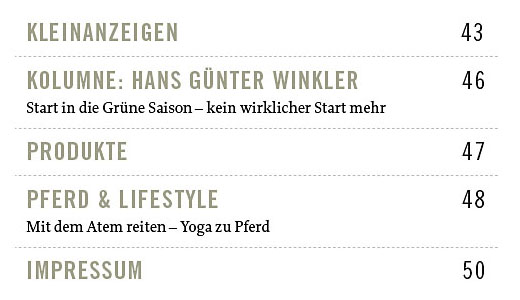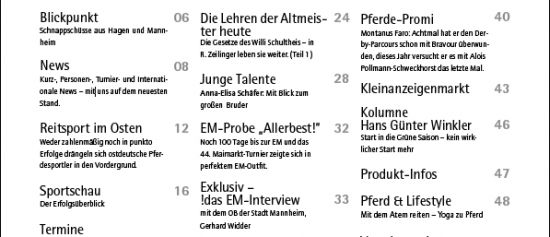
Frage an Typocracks: Zulässig oder besser nicht?
Bei der Gestaltung eines Inhaltsverzeichnisses eines Magazines stehe ich vor der Frage, ob die gewählte Schriftmischung zulässig oder doch ein absolutes "no go" ist:
Eine Rotis Semi Sans 55 (15 Punkt) als Headline mit einer ATQuaySans book (9 Punkt) für den Fließtext?
Eventuelle Alternativen?
Wobei die ATQuay die Standard Schrift des Magazins ist.
Hi nicki, hast du bilder?
Mein erster Reflex bei Rotis ist ja immer ein zartes NEEIIN!! und Quay ist auch sehr eigen.
Die Problematik ist hierbei insgesamt, dass ursprünglich 2 Seiten Inhalt jetzt auf 1 Seite sollen - inclusive Bildern, die ich jetzt obendrüber positioniert habe...
Im Anhang ein Sceenshot von einem Ausschnitt der Seite.
von der quay kann ich wenig erkennen, es scheint aber zu harmonieren. Warum nimmst du nicht auch die Quay in den Überschriften?
Wenn du Platz sparen musst, kannst du bestimmt noch was bei der Anordnung der Seitenzahlen reißen und die Zwischenzeilen halbieren.
...tja - die zweite Schrift war ursprünglich eine "Notlösung", da ich keinen "light"- Schriftschnitt von der ATQuay habe...
Hier nochmal 2 Ausschnitte - vielleicht erkennt man das besser....
Nur als Möglichkeit: Für die Überschriften die Quay und im Text dann Trade Gothic oder News Gothic? So ganz rund laufen die beiden meiner Meinung nach nicht zusammen.
wenn dann eher die trade/news gothic für die headlines ...
im fliesstext ist die quay sicher etwas vorteilhafter!
..o.k. - vielen Dank erstmal - woran kann ich das festmachen, ob etwas harmoniert, oder nicht?
Bei mir ist es oft Gefühlsache - ich würde es aber gerne wissen, eine Regel kennen, ein Gesetz anwenden.
Die Aussagen in Standardwerken sind diesbezüglich nicht einheitlich dargestellt...
Jedenfalls kann ich für mich keine Regel ableiten.
Ein schwieriges Thema.
...hier mal ein Ausschnitt unter Einsatz der vorgeschlagenen Schriften:
Fließtext - ATQuay
Headlines - NewGothicStd.Meduim-13
alternativ:
Headlines - TradeGothic.Medium-13
wichtig ist bei einem schriftmix der kontrast zwischen den schriften.
normalerweise würde ich mich immer schwer tun zwei ähnliche schriften
zu mixen - sinnvoll waere eine antiqua und eine grotesk zu mischen
oder eine relativ neutrale schrift und eine speziellere schrift. wie stark
der kontrast sein sollte haengt von der gestaltungsidee ab ...
soll der kontrast eher geringer ausfallen kann man auf schriften
zurueckgreifen die es als antiqua undgrotesk oder slab serif gibt.
man kann aber auch auf verschiedene schriften des gleichen
schriftgestalters zurueckgreifen und so einen zusammenhang schaffen ...
letztendlich ist das immer ein austesten und probieren ... in deinem
beispiel ist mir der kontrast momentan noch zu gering und ich frage mich
warum du überhaupt zwei schriften mischen willst. um den unterschied
zu verstärlen könntest du die trade in versalien und bold setzen ...
Antwort an Microboy: Danke für das Beispiel - das ist wirklich krass, ich glaube für einen "Inhalt" zu heftig - dann versuche ich vielleicht doch lieber die ATQay in light bzw. hairline o.ä. aufzutreiben...Trotzdem danke!! :-)
Was, bitte, ist an Microboy's Beispiel krass??? :shock:
(mal abgesehen davon, dass seine Skizze eine ganz krasse Verbesserung ist ...)
Hier meldet sich ein "Konsument":
In einem Register will ich schnell die Seitenzahl auffinden, und wenn ich einen Artikel später wieder suche, sind Titel und Untertitel hilfreich. Ich merke das beim Spiegel, den ich als Nach-benutzer unregelmäßig kriege. Das Inhaltsverzeichnis da funktioniert gut, hat Ähnlichkeit mit Microboys Vorschlag.
Das gezeigte Beispiel von Microboy ist ein Vorzeigebeispiel, wie es im Buche steht! Aber in Bezug auf meine Anwendung in meinem Inhaltsverzeichnis ist mir persönlich der Kontrast zu stark.
Außerdem steht das Layout des Magazins und das Inhaltsverzeichnis muss sich meiner Meinung nach irgendwie daran anpassen.